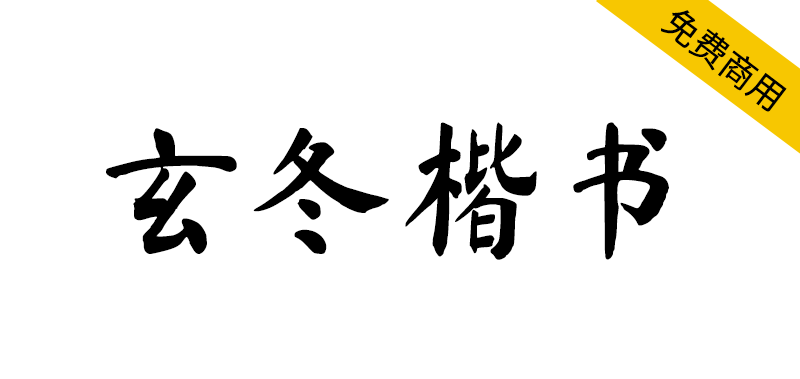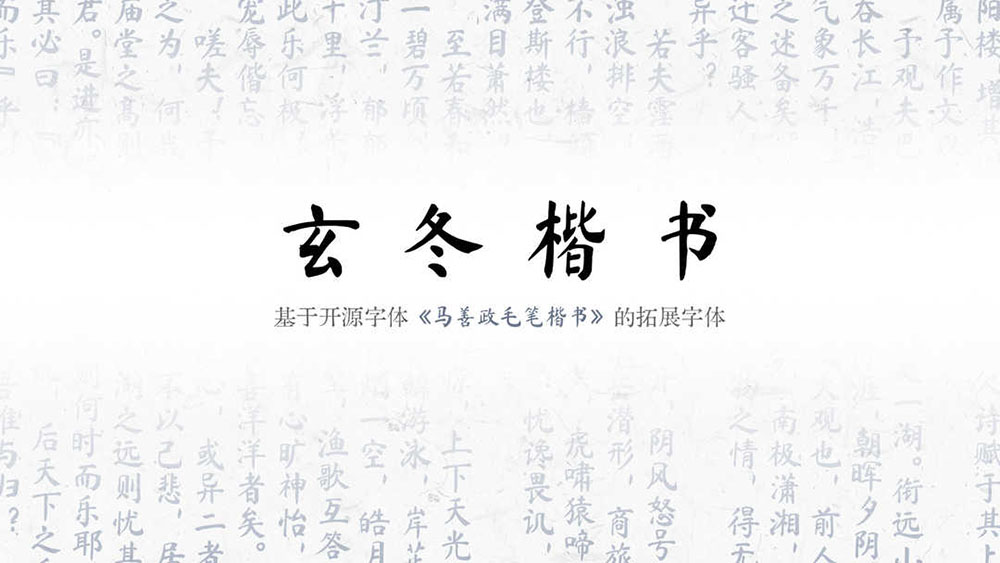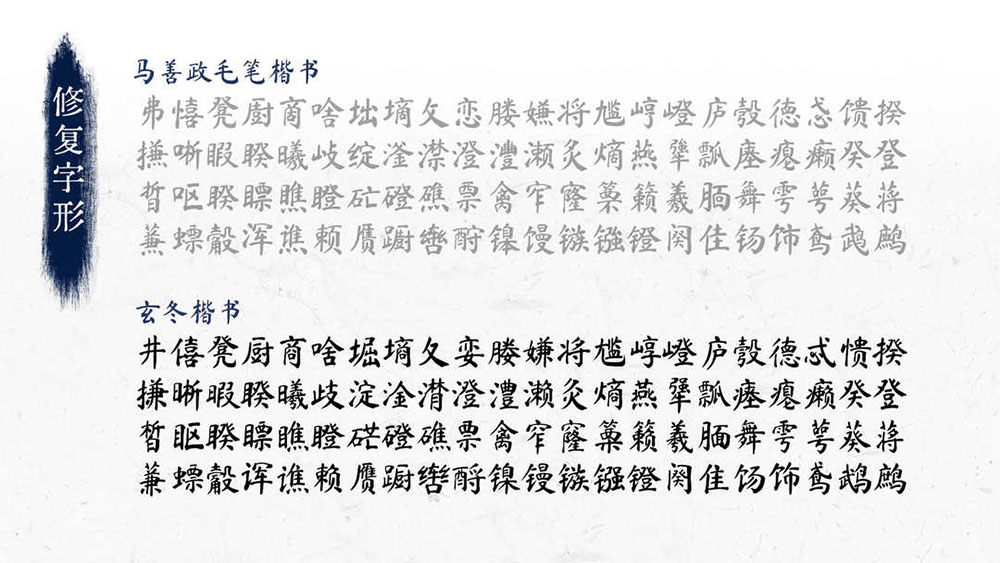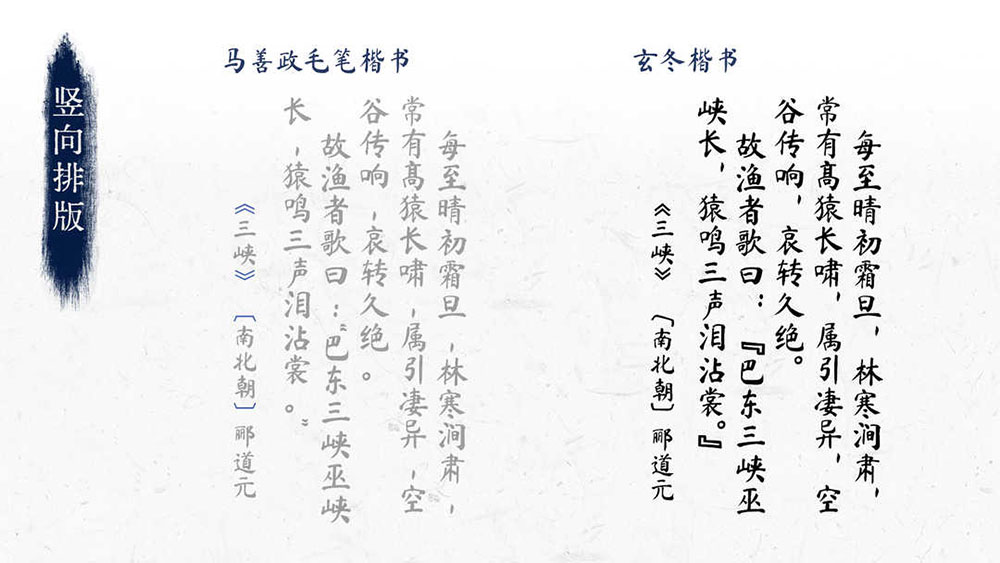
玄冬楷书是基于开源字体《马善政毛笔楷书》的拓展字体。在原版的基础之上修复了错误的字形并添加竖排排版的特性。
修复以下88字:井僖凳厨商啥堀墒夂娈媵嫌将尴崞嶝庐彀德忒愦揆搛晰暇睽曦歧淀淦潸澄澧濑灸熵燕犟瓢瘗瘪癞癸登
皙眍睽瞟瞧瞪硭磴礁票禽窄窿篥籁羲腼舞雩萼葵蒋蒹螵觳诨谯赖赝蹰辔酹镍镘镞镪镫阕隹饧饰鸢鹉鹧。
调整都分汉字字面的问题。增加 vert 特性,用于竖向排版。新增“啰瞭”二字,补全一级通用规范字。